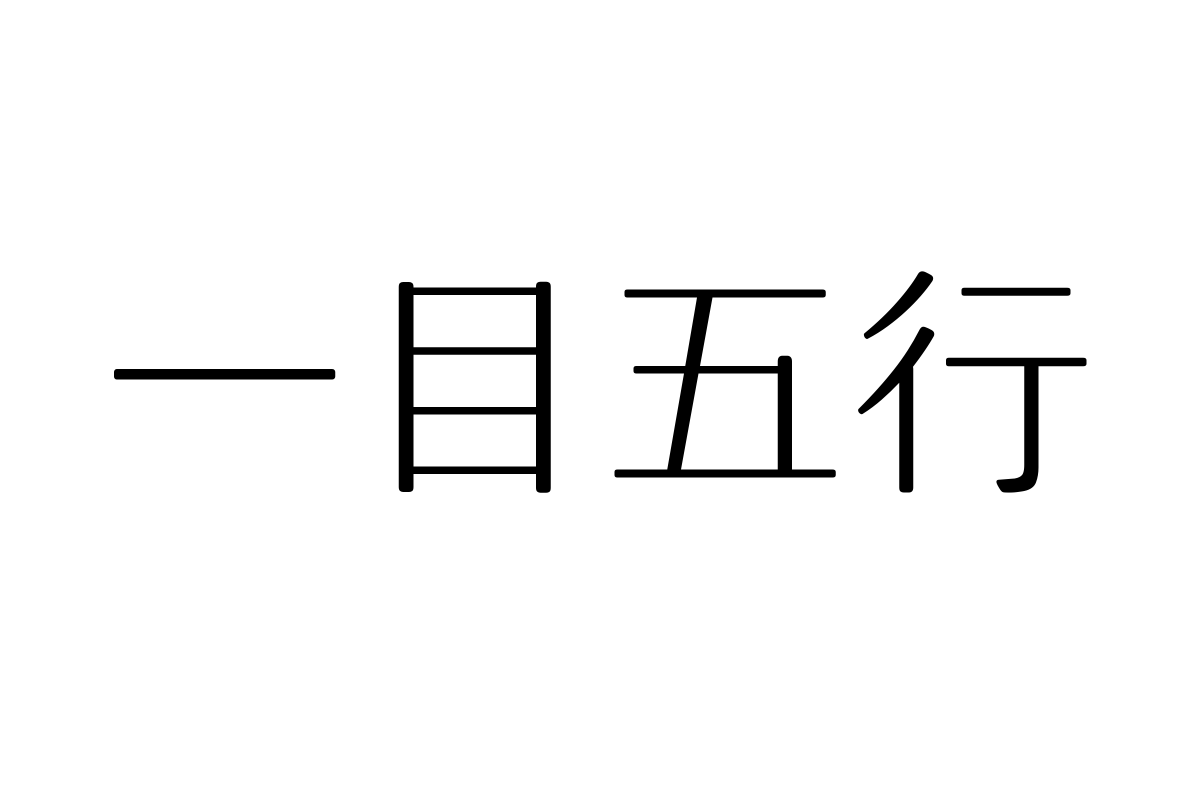
汉仪润圆-35是一款具有现代感和时尚感的中文字体,适用于各种商业、广告、设计等领域。这款字体的特点在于其简洁而富有力量的设计,线条流畅,结构紧凑,给人一种清晰、易读的感觉。同时,它的笔画粗细适中,既不会显得过于繁琐,也不会显得过于简单,能够很好地满足不同设计需求。
此外,汉仪润圆-35还具有一定的艺术感,线条的弯曲和转折都经过精心设计,使得整个字体看起来既有美感又不失实用性。无论是用于标题、正文还是装饰元素,都能够展现出独特的风格和个性。
总的来说,汉仪润圆-35是一款非常实用的中文字体,无论是在商业、广告还是设计领域都有着广泛的应用前景。